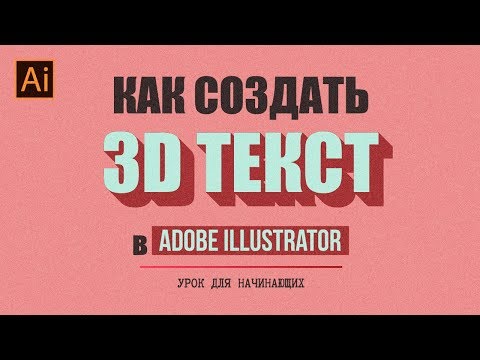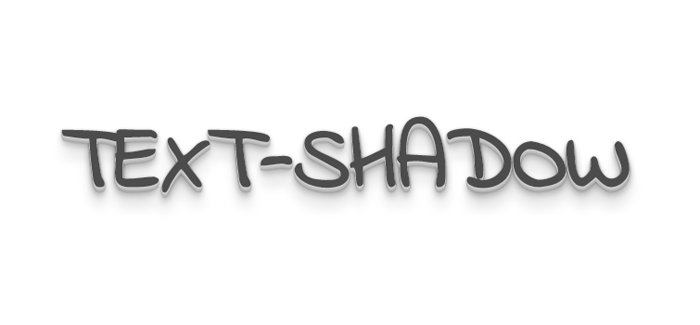
Создание шрифта с тенью: полезные советы и идеи для красивого оформления текста
Шрифт с эффектом тени - это отличный способ придать тексту стиль и выразительность. В данной статье представлены советы и идеи по созданию шрифта с тенью, которые помогут вам в создании красивого и уникального дизайна.
Выберите подходящий шрифт: для создания эффекта тени лучше всего использовать жирные и пропорциональные шрифты. Они лучше выделяются и создают глубину.
Используйте ровную, но небольшую тень: при добавлении тени к шрифту важно подобрать правильное расстояние и интенсивность тени. Ровная, но небольшая тень добавляет объем и глубину.
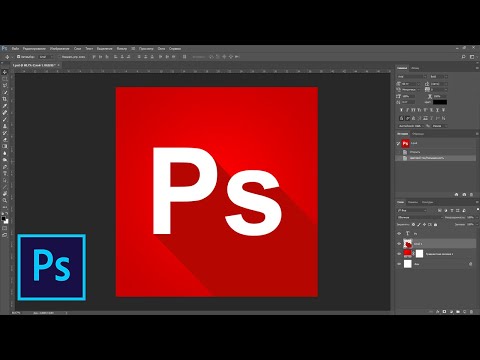
Экспериментируйте с цветом тени: игра со светлыми и темными оттенками при добавлении тени к шрифту поможет создать интересный и оригинальный эффект. Попробуйте разные комбинации цветов.